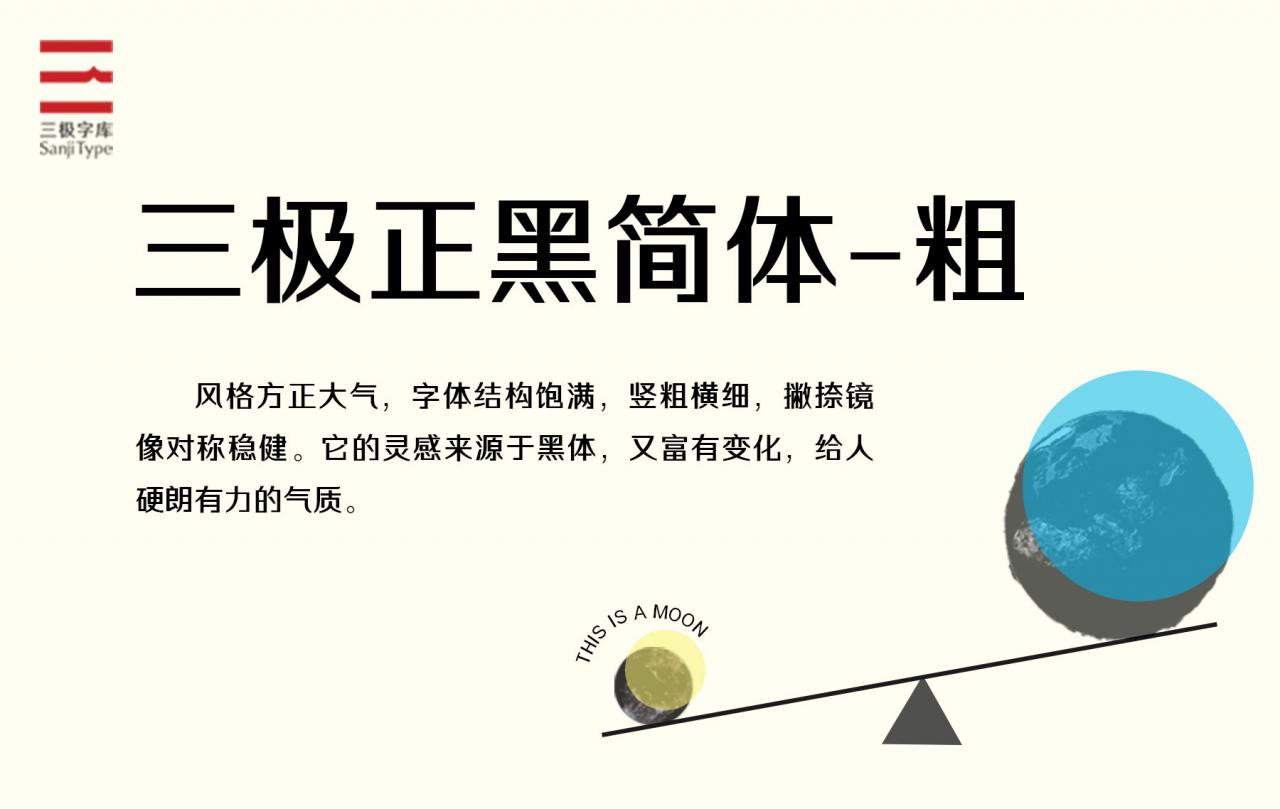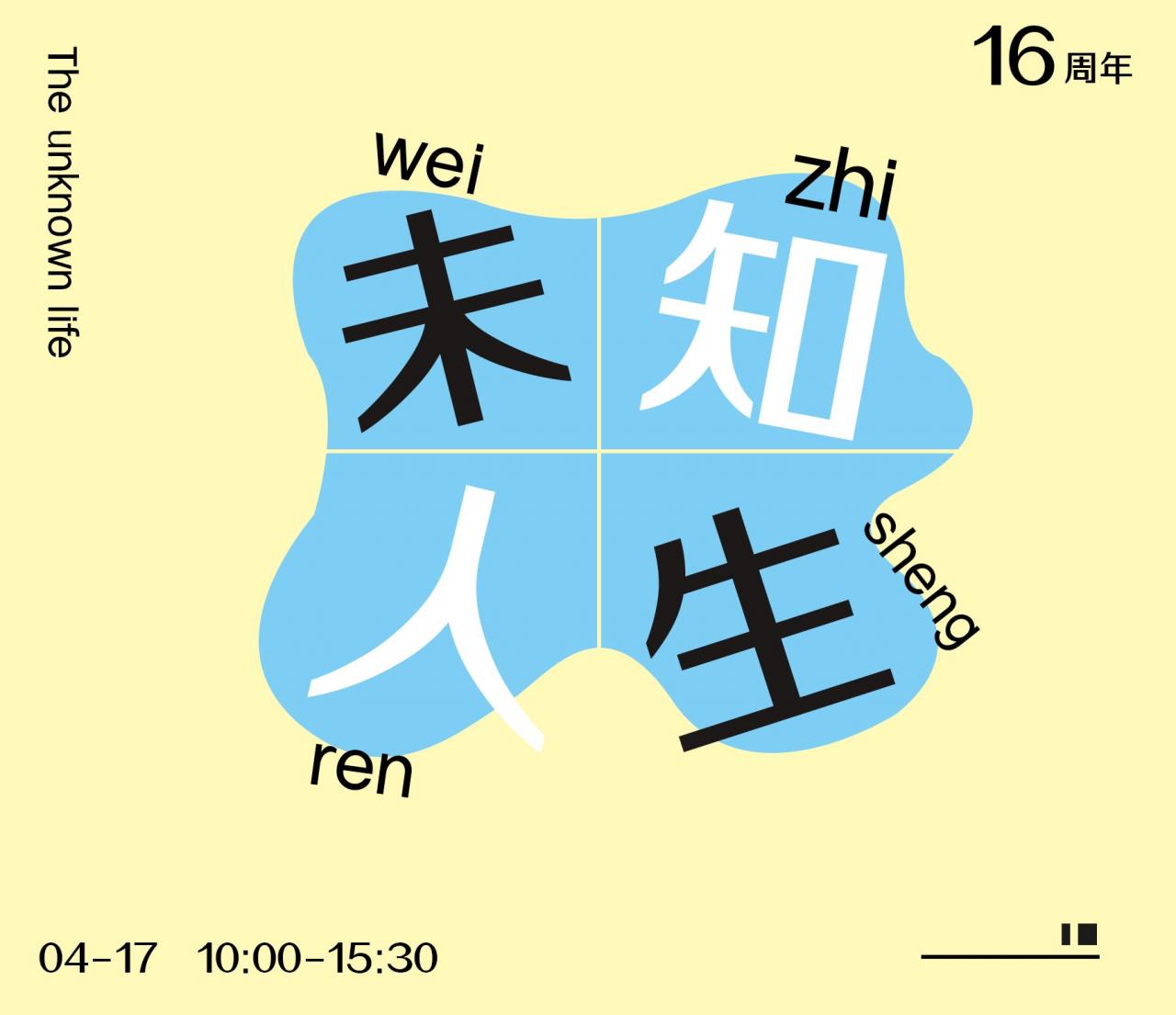
三极正黑简体-粗
字体名称:三极正黑简体-粗
设计师:王荣诚
所属分类:黑体
三极正黑简体作品整体风格方正大气,字体结构饱满,竖粗横细,撇捺镜像对称稳健。它的灵感来源于黑体,又富有变化,给人硬朗有力的气质。视觉效果简洁易识别,实用性强。本作品适用于传统印刷媒介的标题与正文排版、各类屏幕显示及影视字幕等。
适用媒介:报纸、杂志、书籍、广告、标志、宣传册、空间导视、包装、影视、屏幕显示、交互设计等媒介。